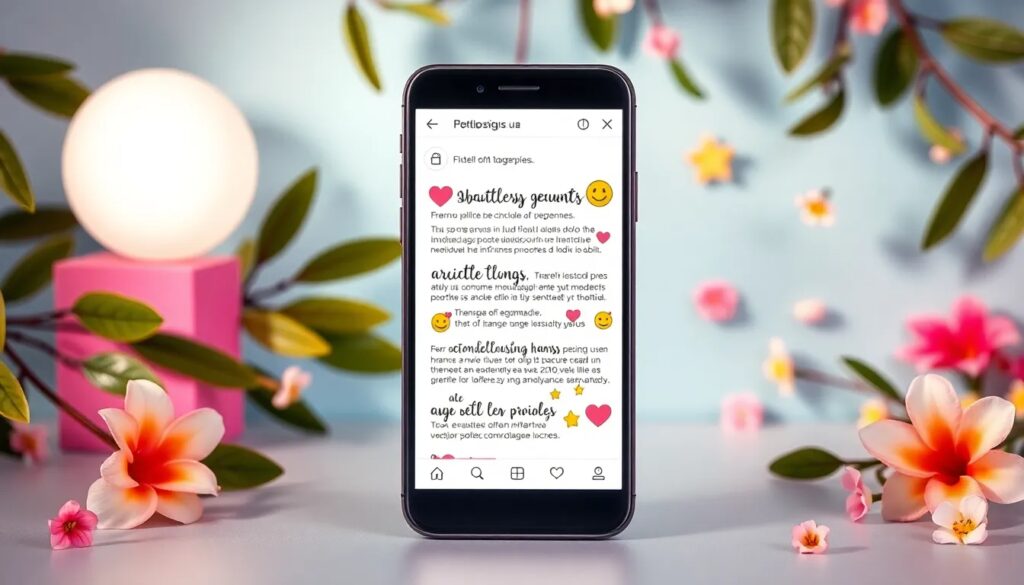
Fonts for instagram bio: generador y estilos para usar
En el mundo de Instagram, la biografía es uno de los elementos más relevantes para atraer la atención de tus seguidores. Utilizar fonts for instagram bio adecuadas puede marcar la diferencia entre un perfil común y uno que realmente destaque. En este artículo, exploraremos todo lo que necesitas saber sobre cómo personalizar tu biografía de Instagram.
Las fuentes para Instagram son una herramienta poderosa que te permite expresar tu creatividad y personalidad. Desde caracteres únicos hasta estilos de texto elegantes, aprender a utilizarlas correctamente te ayudará a resaltar tu perfil entre la multitud.
¿Qué son las fuentes para Instagram?
Las fuentes para Instagram son estilos de texto que puedes utilizar para personalizar tu biografía, publicaciones y comentarios. Estos estilos pueden ser creados a partir de caracteres Unicode, que son códigos que representan diferentes símbolos y letras.
El uso de estas fuentes no solo embellece tu perfil, sino que también permite que tu biografía sea más legible y atractiva. En lugar de utilizar el texto convencional, puedes optar por fuentes que reflejen tu estilo personal.
Además, las fuentes son una manera de hacer que tu perfil destaque. Con tantas cuentas compitiendo por la atención del público, un toque creativo puede ser el impulso que necesites.
¿Cómo funciona un generador de fuentes para Instagram?
Un generador de fuentes para Instagram es una herramienta en línea que te permite crear estilos de texto personalizados. A través de este generador, puedes ingresar el texto que deseas transformar y elegir entre diferentes estilos de fuentes.
Estos generadores utilizan caracteres Unicode para crear variaciones de texto que puedes copiar y pegar directamente en tu biografía de Instagram. La mayoría de ellos son fáciles de usar y ofrecen una amplia variedad de estilos, desde cursivos hasta negritas.
Para utilizar uno de estos generadores, simplemente sigue estos pasos:
- Visita un generador de fuentes en línea.
- Introduce el texto que deseas personalizar.
- Selecciona el estilo de fuente que prefieras.
- Copia el texto generado y pégalo en tu biografía de Instagram.
¿Cuáles son los estilos de fuentes más populares para Instagram?
Existen múltiples estilos de fuentes que puedes utilizar en tu biografía de Instagram. Algunos de los más populares incluyen:
- Fuentes cursivas: ideales para dar un toque elegante.
- Fuentes en negrita: perfectas para destacar información clave.
- Fuentes monoespaciadas: suelen dar un aire retro o técnico.
- Fuentes decorativas: opciones creativas que agregan un toque único.
- Fuentes con símbolos: que incorporan emojis o signos especiales.
La elección del estilo dependerá de tu personalidad y del mensaje que desees transmitir. Recuerda que menos es más; un exceso de estilos puede hacer que tu biografía se vea desordenada.
¿Cómo puedo usar fuentes para mi biografía de Instagram?
Para usar fonts for instagram bio, simplemente sigue estos pasos:
- Selecciona un generador de fuentes en línea.
- Ingresa el texto que deseas personalizar.
- Elige el estilo que más te guste.
- Copia el texto generado.
- Pégalo en tu biografía de Instagram.
Es importante que revises cómo se ve tu biografía después de hacer los cambios. Algunas fuentes pueden no ser completamente compatibles con la plataforma, así que asegúrate de que tu texto sea legible y atractivo.
¿Qué tipos de caracteres Unicode se pueden utilizar en Instagram?
Los caracteres Unicode son la base de las fuentes personalizadas. Instagram permite utilizar una variedad de caracteres, como:
- Letra en negrita y cursiva.
- Símbolos especiales y emojis.
- Caracteres de diferentes alfabetos (griego, cirílico, etc.).
- Marcas de puntuación únicas.
Usar estos caracteres no solo embellece tu perfil, sino que también te permite jugar con diferentes estilos y representar mejor tu personalidad. No olvides que algunas fuentes pueden no ser visibles para todos los usuarios, así que elige sabiamente.
Si quieres compartir tu estilo único de fuentes en otras redes sociales, la mayoría de las plataformas permiten copiar y pegar texto de manera similar a Instagram. Aquí tienes algunas recomendaciones:
- Usa el mismo generador de fuentes para crear contenido para Facebook, Twitter y TikTok.
- ¿Qué tipos de caracteres Unicode se pueden utilizar? Se pueden usar letras en negrita, cursiva, símbolos y emojis.
Utilizar fuentes personalizadas en Instagram no solo embellece tu perfil, sino que también te permite destacar y comunicar mejor tu identidad. ¡Empieza a experimentar con diferentes estilos y sorprende a tus seguidores!